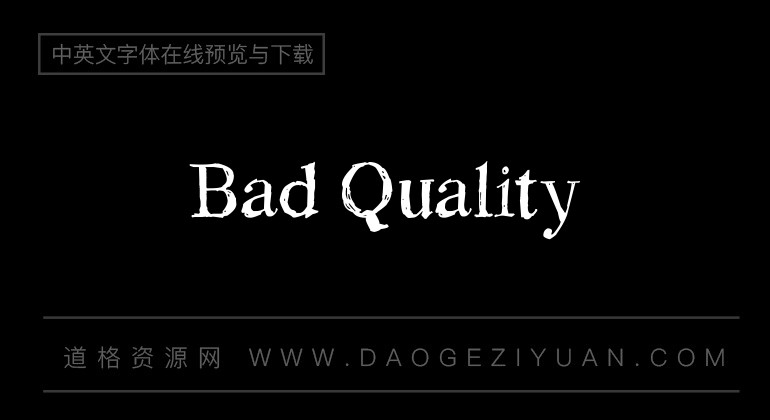
Bad Quality 字体是一种古老的文字形式,它是在中国古代创作的,有着模糊的线条和模糊的轮廓。它的特点是字符形状不太明显,字体也比较模糊,字符之间的间距也比较大,而且字体的细节也比较粗糙。这种字体可以用来记录历史,也可以用来装饰和设计,但是它们不太适合用来阅读,因为字体模糊,字符之间的间距也大。内容介绍
Bad Quality是一款非常不错的手写艺术字体,具有很好的视觉感,适合于文化类的宣传设计、商业类品牌的广告和产品包装设计以及个性化文字排版等较多场景。